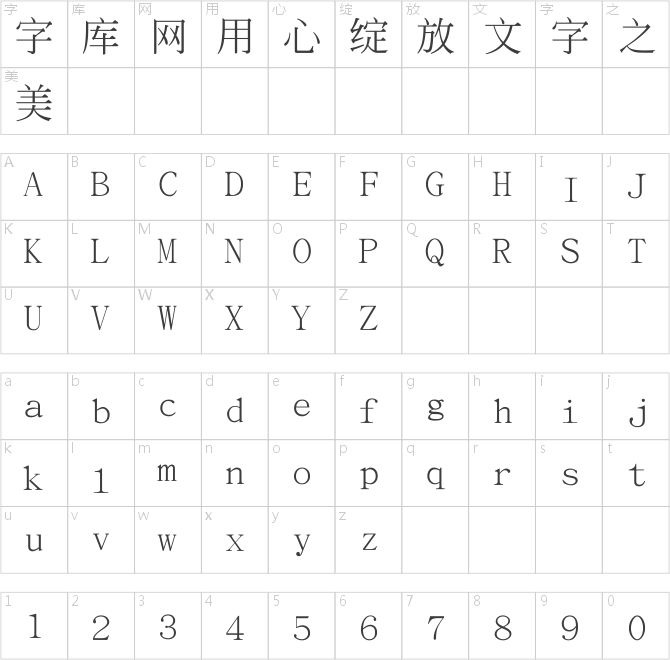
字体名称: 文鼎书宋简繁
文鼎书宋简繁
文鼎书宋的简体和big5、gb2312繁体合并成了文鼎书宋简繁,二次修订时补了缺失的三个字符并加入了7个二简字,三次修订时修复了postscript名称重名的情况。该字体向上兼容新版win10。
更新Power TrueType Version 5.0版,和原Power TrueType Version 4.0或Power TrueType Version 4.5版本相比又将原Power TrueType big5的扩展471个外字集的部分没有映射字码点的汉字进行了对号入座,并修复『?』字误映射到『抝』字位置的错误。